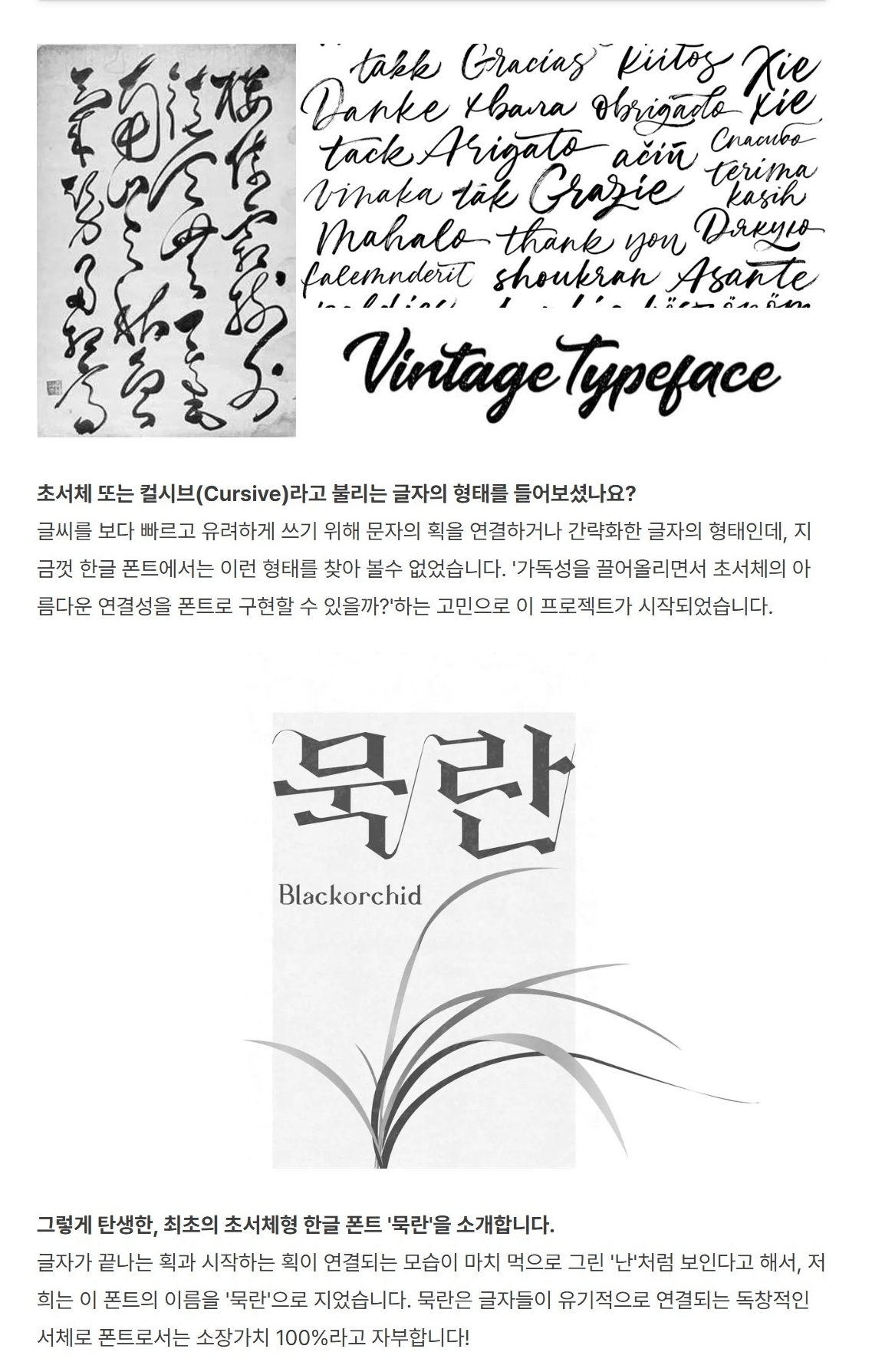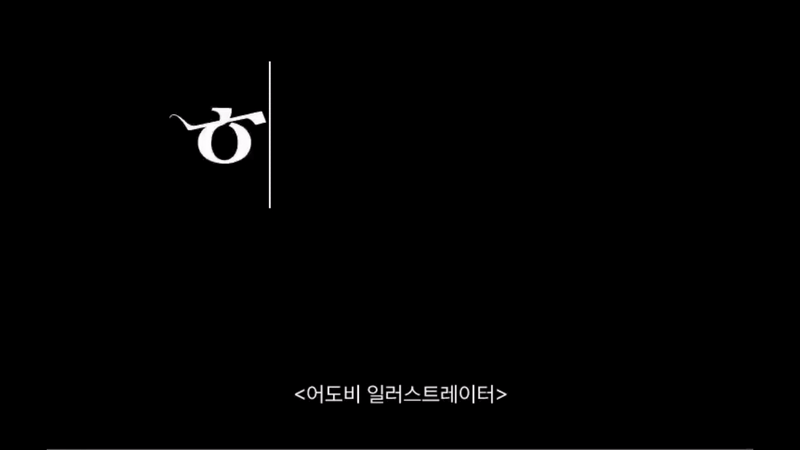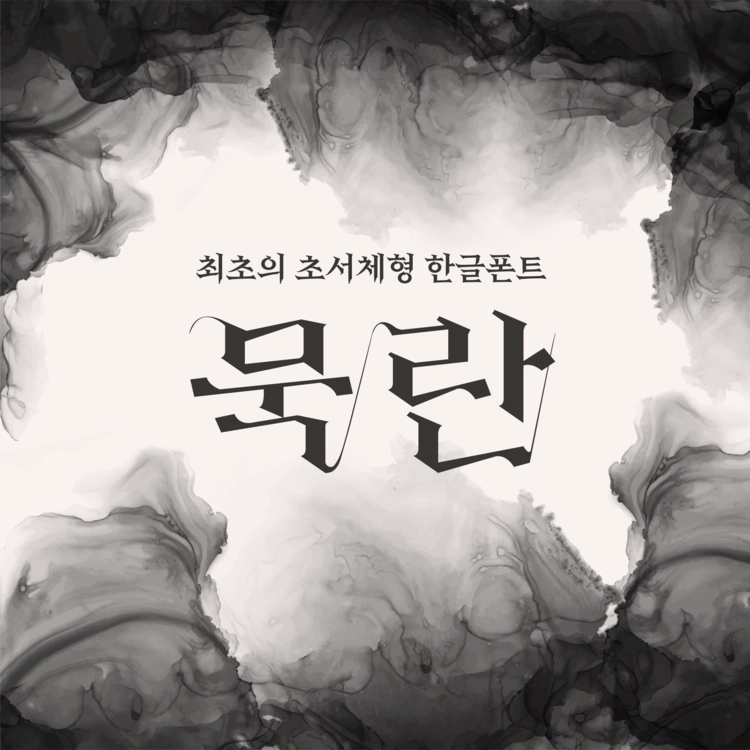
묵란
최초의 초서체형 한글 폰트 '묵란'을 소개합니다. 글자가 끝나는 획과 시작하는 획이 연결되는 모습이 마치 먹으로 그린 '난'처럼 보인다고 해서, 저희는 이 폰트의 이름을 '묵란'으로 지었습니다. 타이핑하다 보면 자연스레 연결되는 글자들이 정말 아름답습니다. '묵란'은 동양 서예의 아름다움과 현대적인 타이포그래피 기술을 접목해, 고전적이면서도 세련된 비주얼을 완성했습니다. 묵란은 글자들이 유기적으로 연결되는 독창적인 서체로 폰트로서는 소장가치 100%라고 자부합니다!